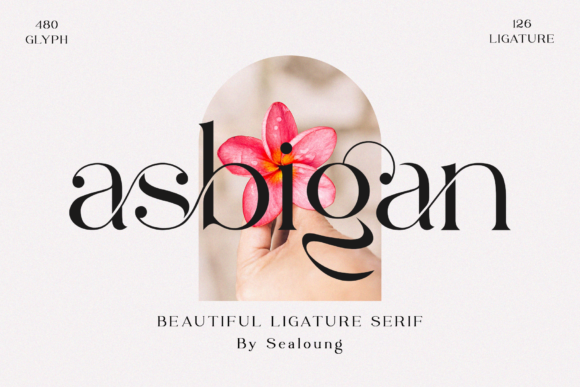
Creativefabrica Asbigan Font 2021
[Creativefabrica] Asbigan Font (2021)
Asbigan - красивый, элегантный и нежный шрифт с засечками.
Он добавит роскошную искру в любой дизайнерский проект, который вы хотите создать!